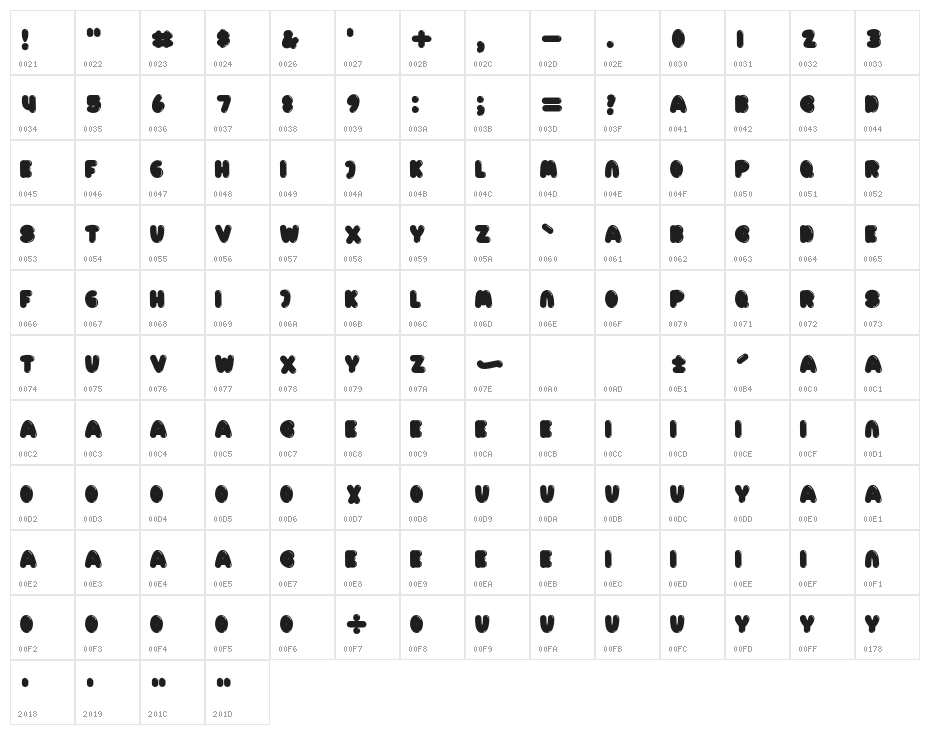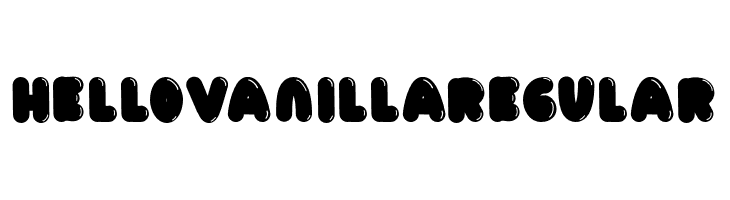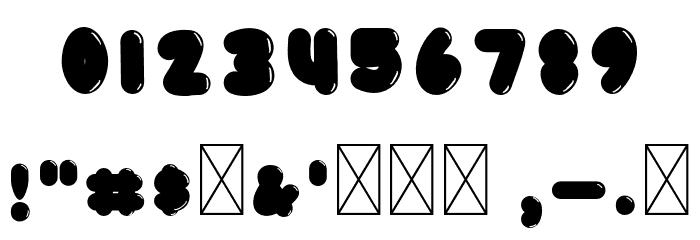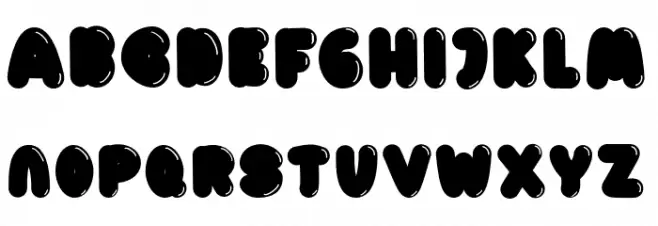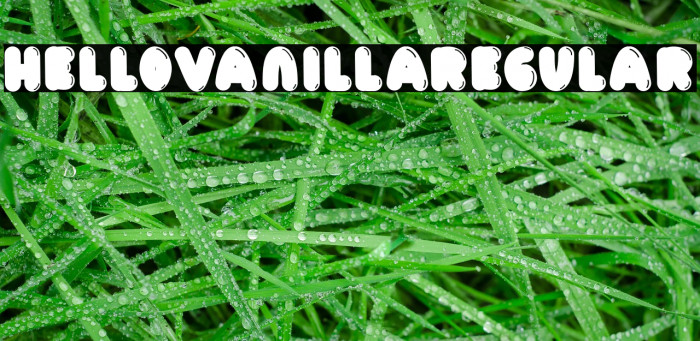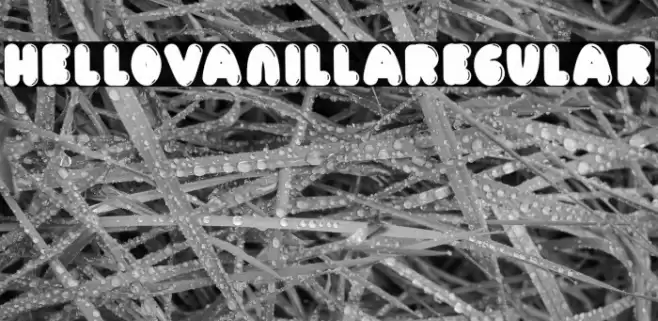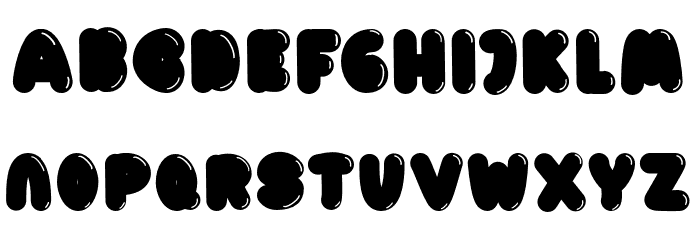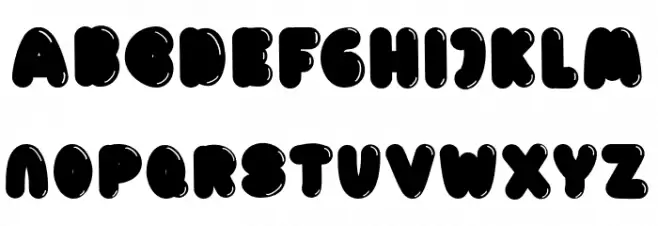
HelloVanillaRegular Font
✎ Cartoon
| Familia de fuentes | Hello Vanilla |
| Categorías | Cartoon |
| Estilo general | Playful, Whimsical |
| Proyectos propuestos | Ideal for children's books, party invitations, playful branding, and any project needing a fun, eye-catching typeface. |